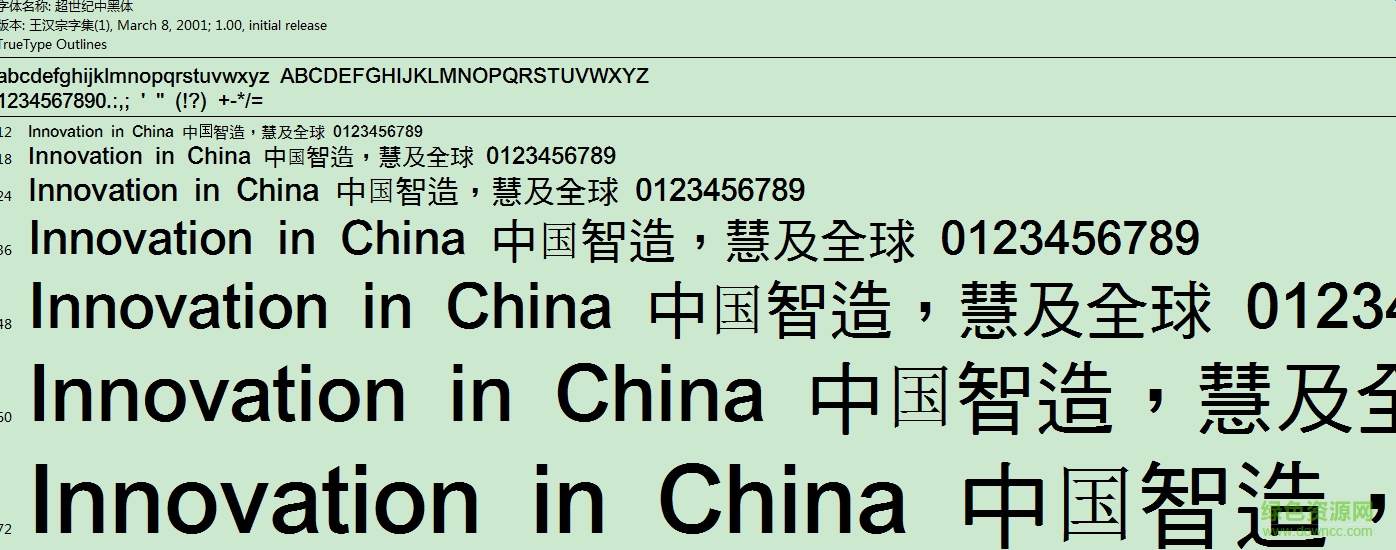
超世紀(jì)中黑體是一款中黑體藝術(shù)字體,表現(xiàn)為寫(xiě)法方正,剛正不阿,看起來(lái)十分的有氣勢(shì),而且字體打印出來(lái)肯定十分的大氣,適合作為報(bào)紙、廣告頁(yè)標(biāo)題使用。小編為大家?guī)?lái)免費(fèi)下載地址。歡迎大家來(lái)綠色資源網(wǎng)踴躍下載哦!